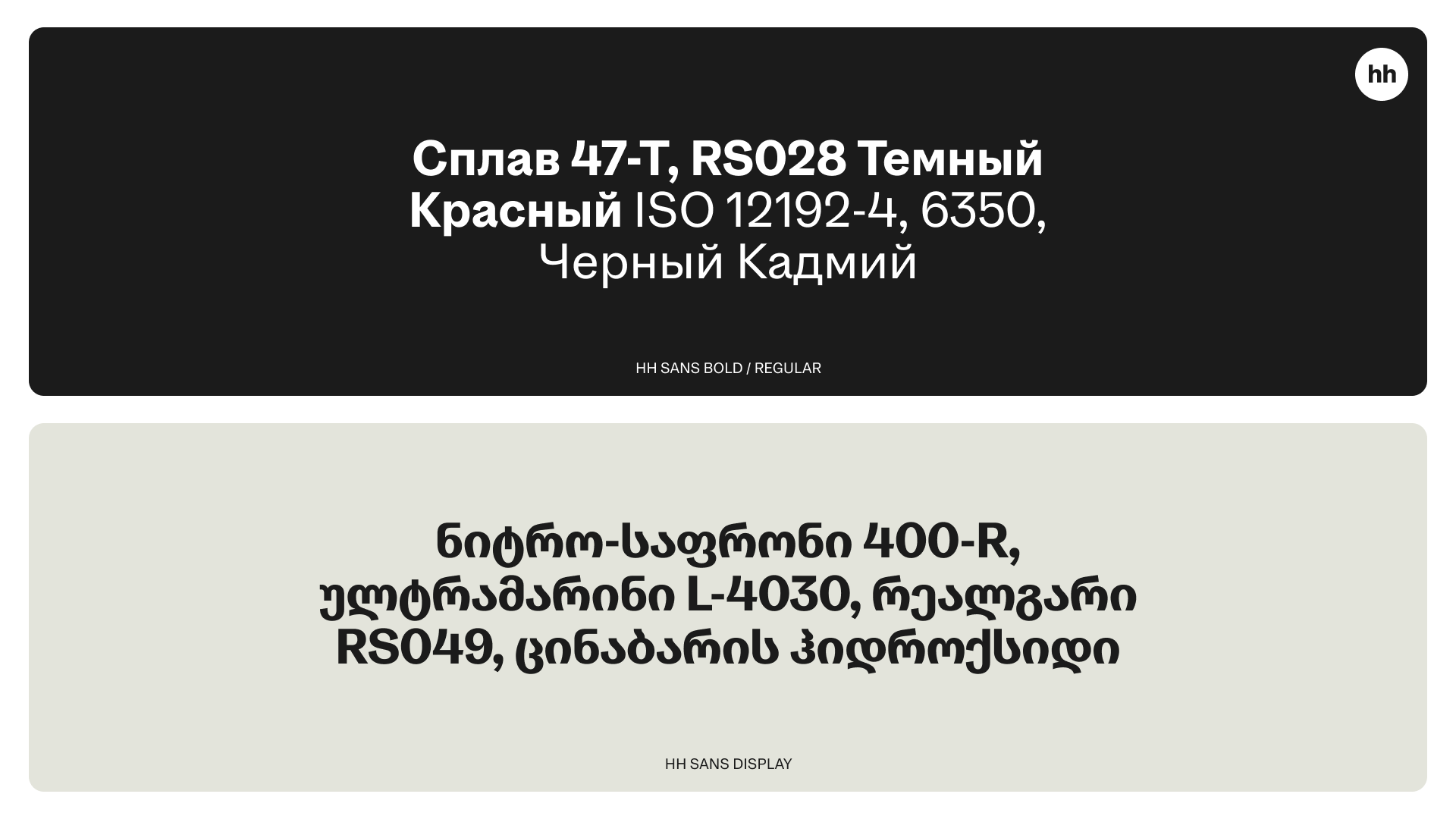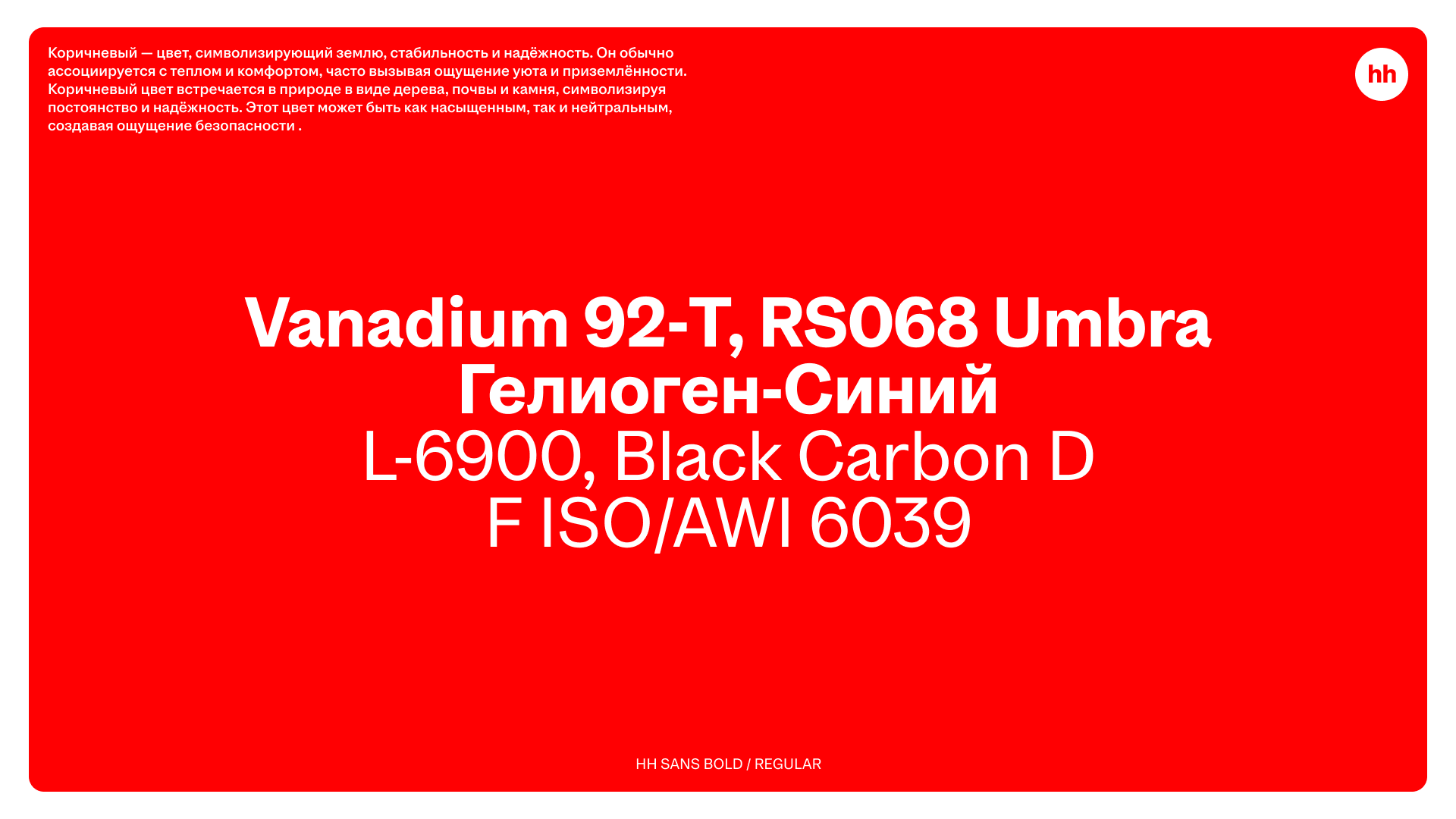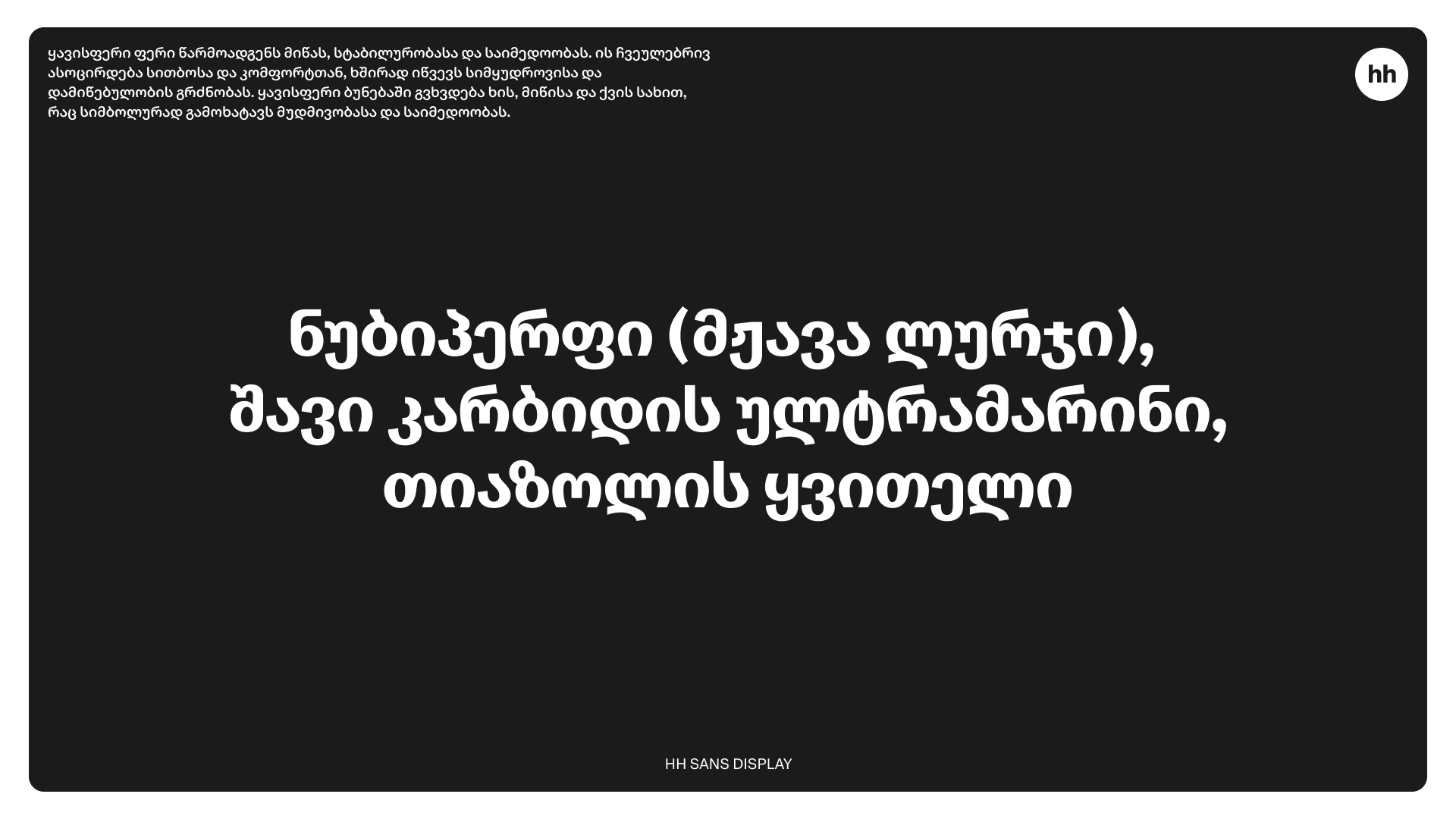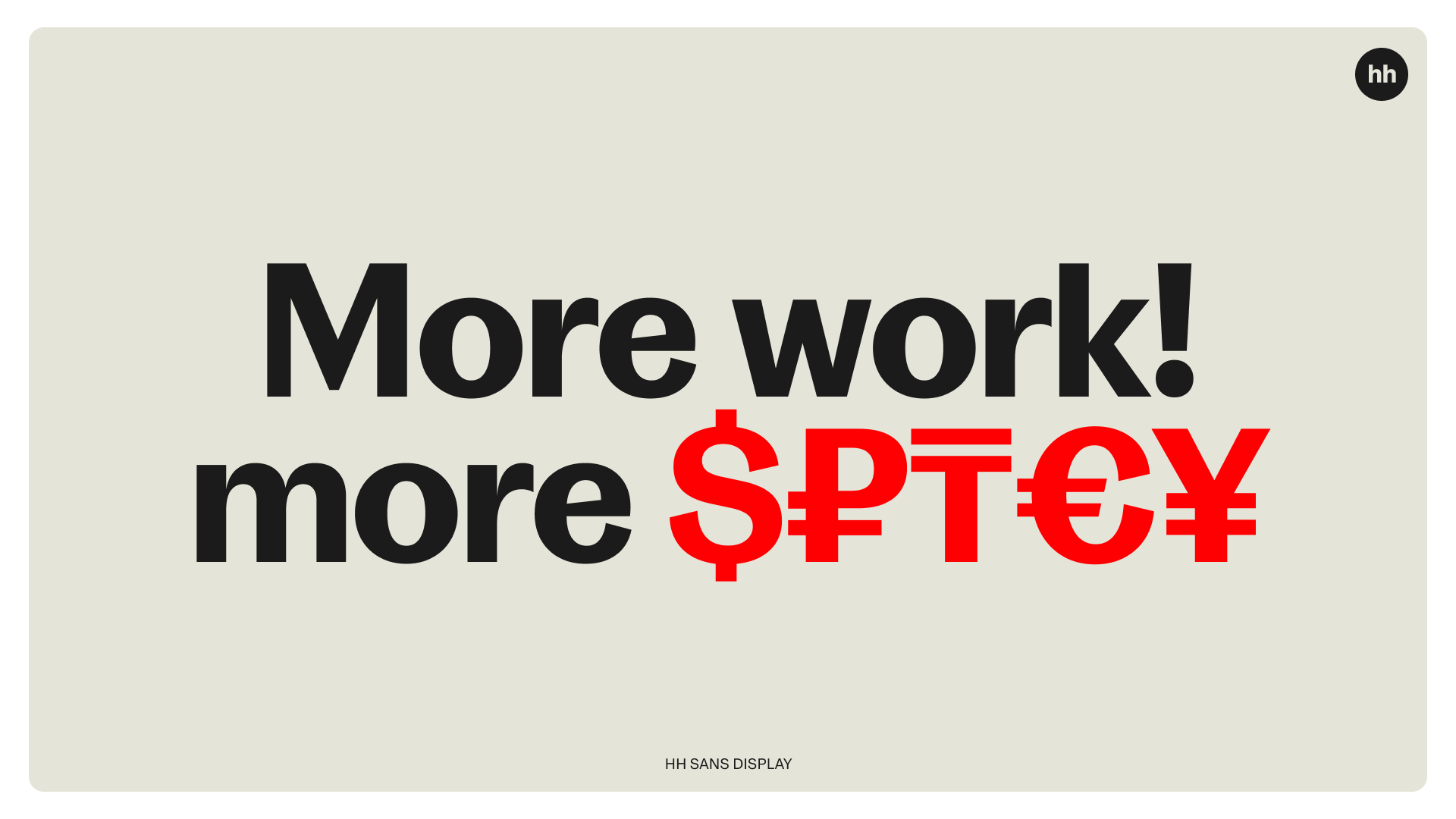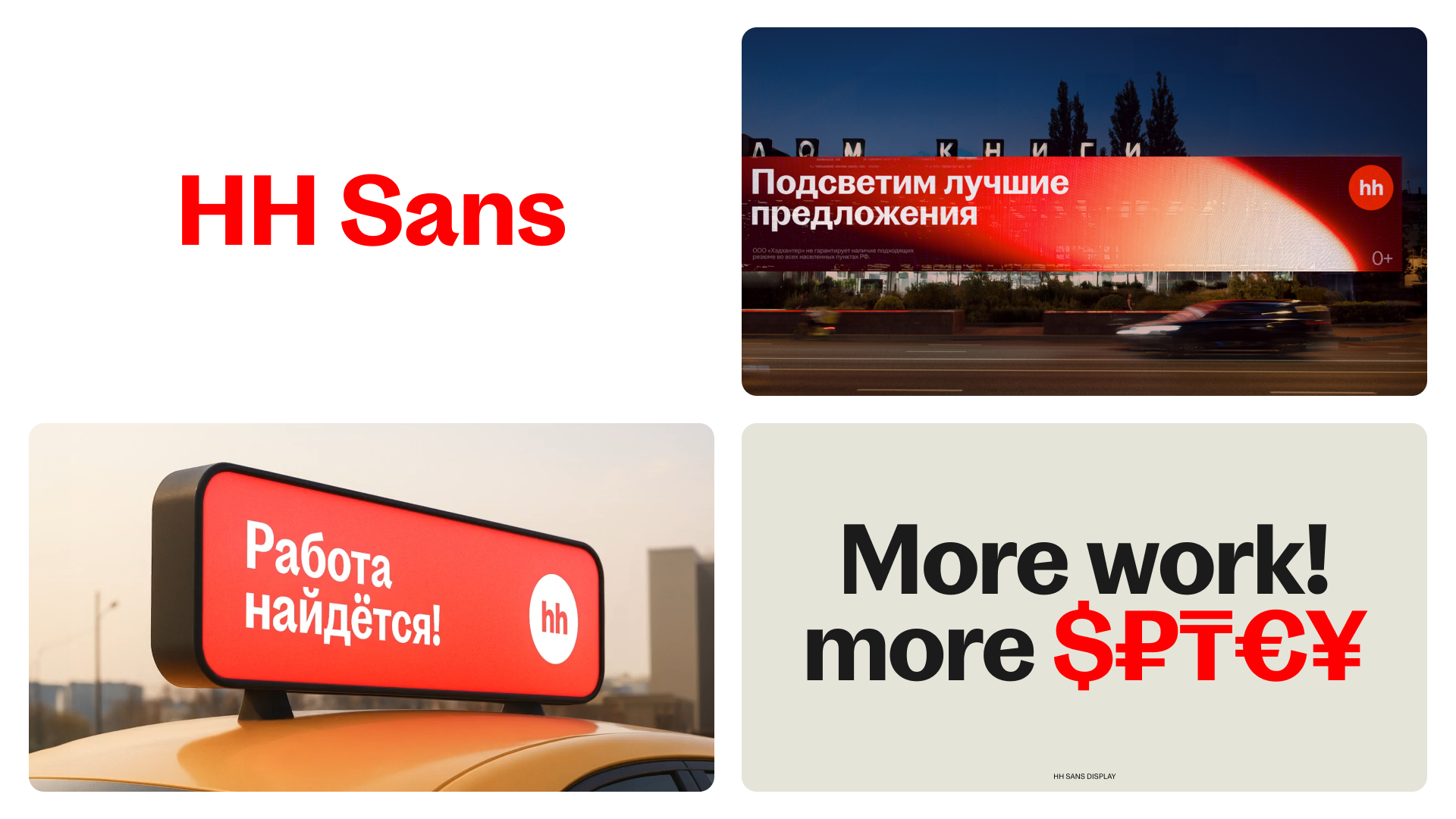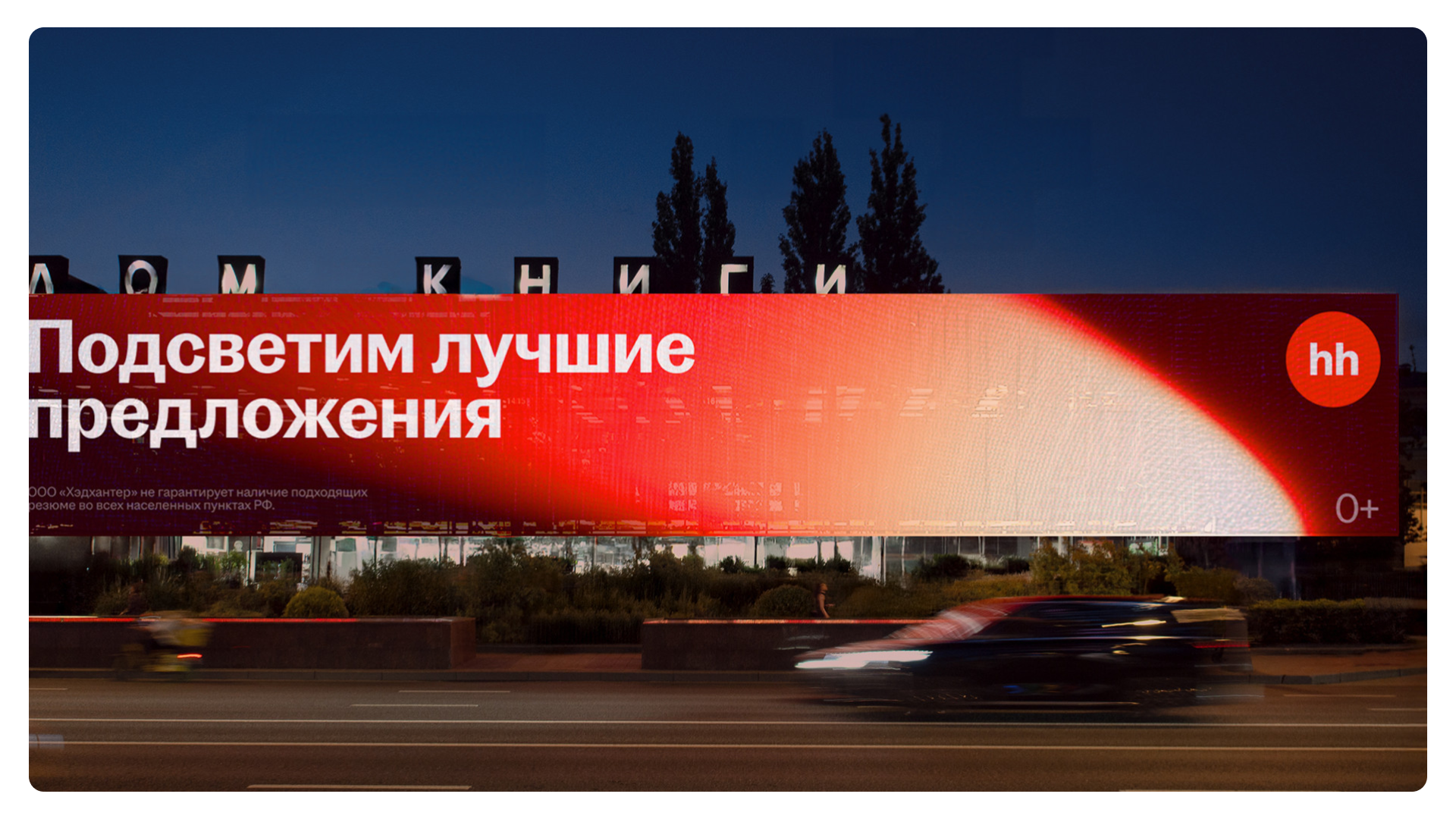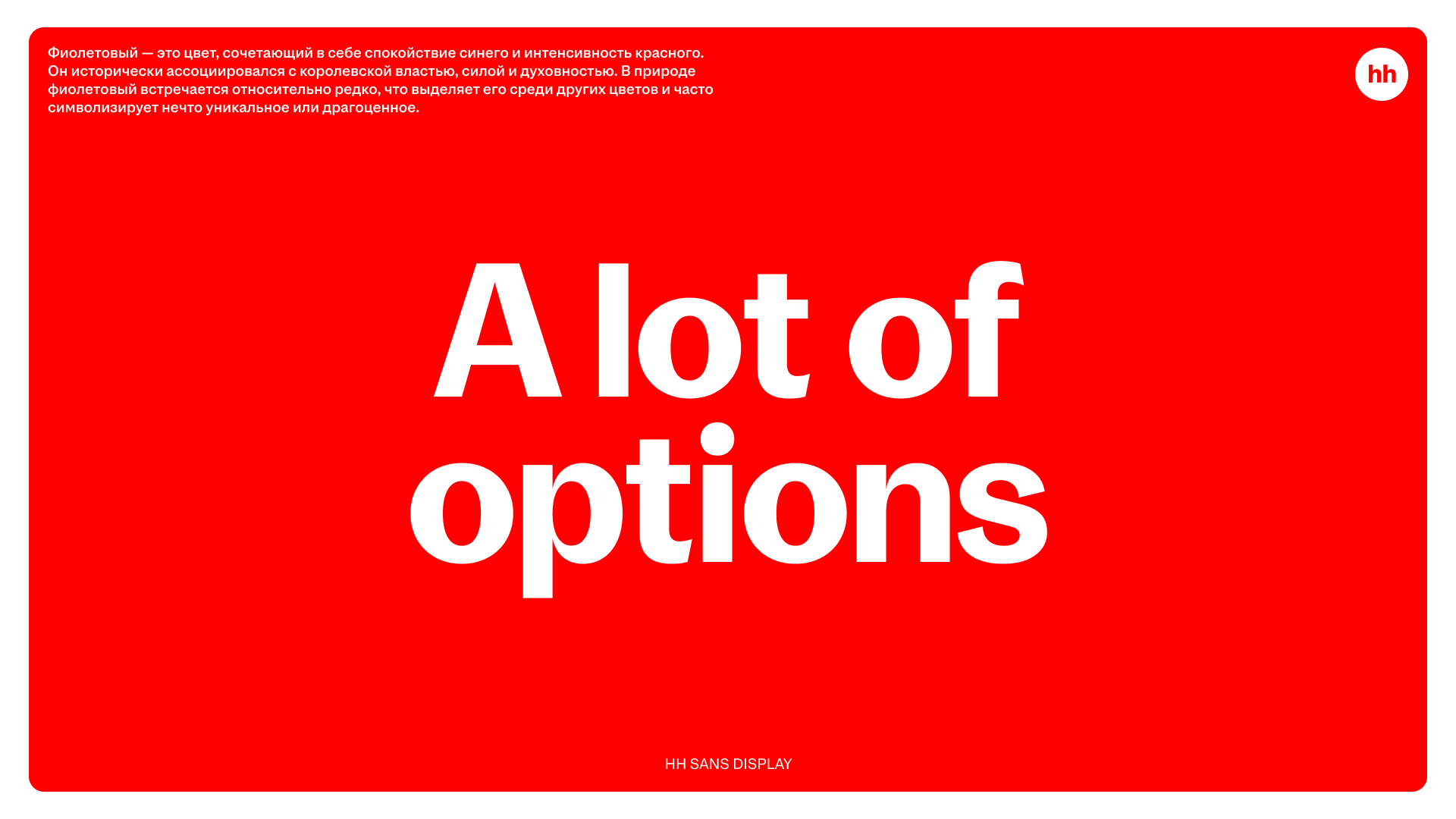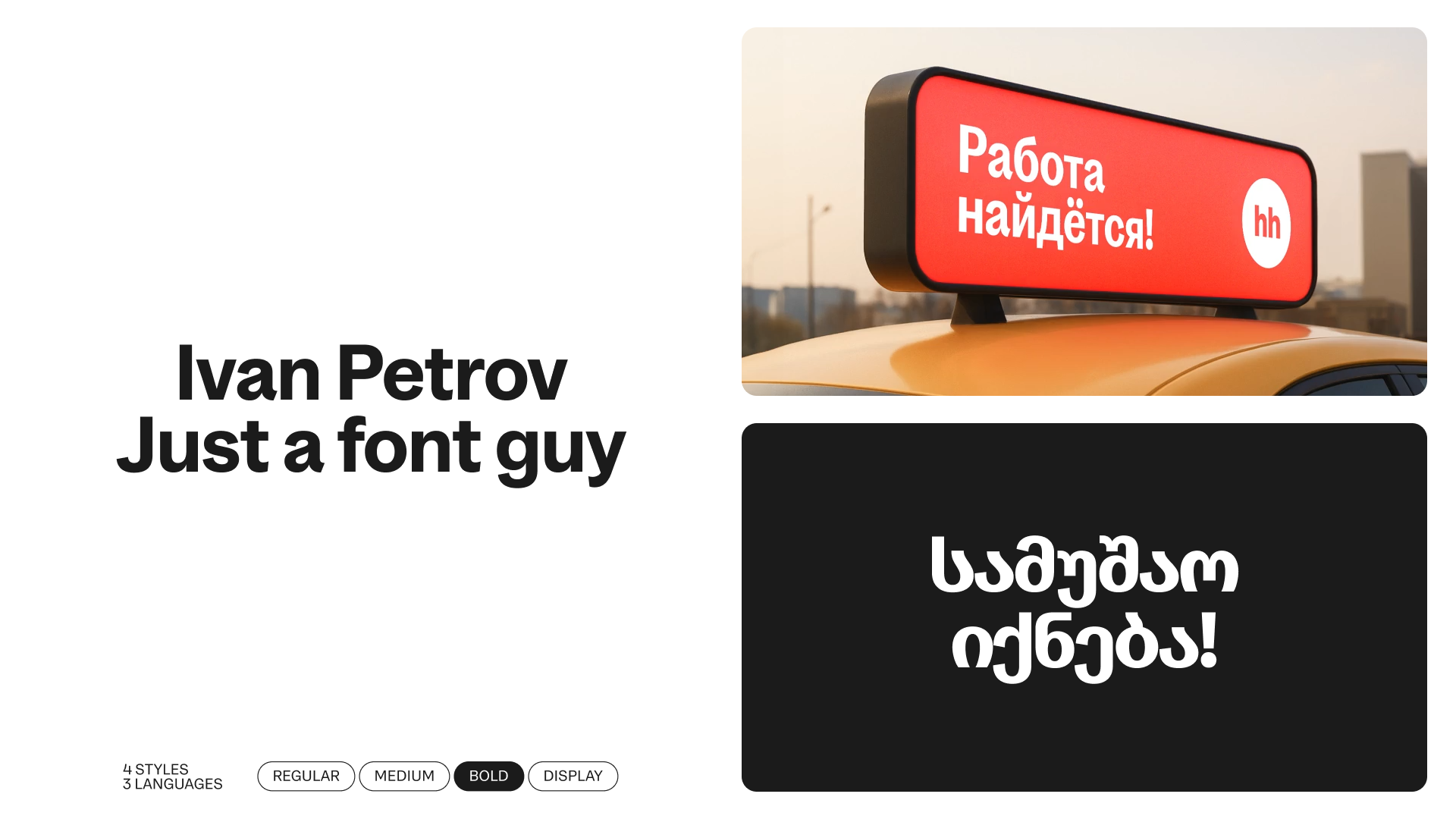
Заказной шрифт
hh sans — гротеск для Head Hunter
Описание работы
В рамках ребрендинга HeadHunter мы разработали hh sans — фирменный шрифт, отражающий обновлённый характер бренда.
Основой послужили американские гротески начала XX века с лёгкой неровностью, живыми формами и плотным ритмом, что придало образу бренда живость и человечность.
Набор включает три текстовых начертания и яркое дисплейное, которое используется в заголовках. Поддержка расширенной латиницы, кириллицы и грузинского алфавита делает hh sans универсальным инструментом для бренда с широкой географией.
Head Hunter
ONY
Сергей Лавриненко, Креативный директор
Линда Косичкина, Арт-директор
Иван Петров, Шрифтовой дизайнер